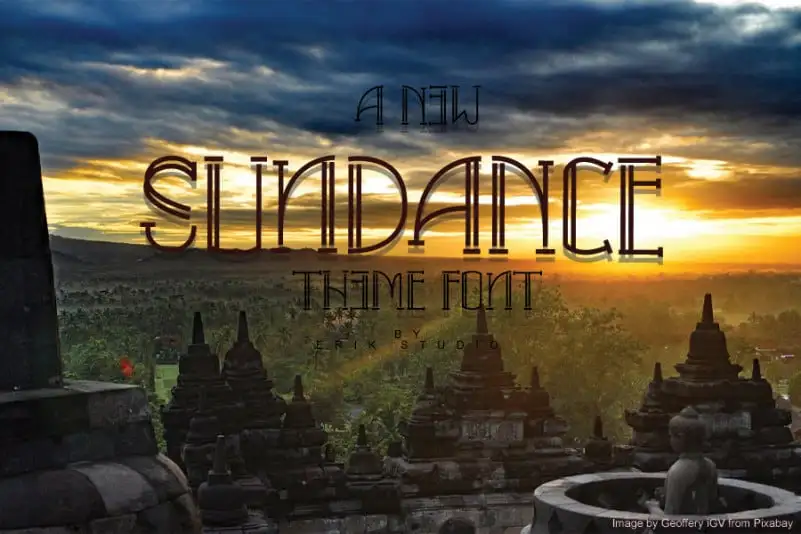
Sundance Display Font – Fonte Grátis
Sundance Display Font
A Sundance Display Font é uma nova adição para designers amadores e profissionais que buscam dar vida a suas criações com estilo. Inspirada por elementos de design outdoor, essa fonte desliza pela tela como um balão de futebol vibrante em pleno céu azul. Suas letras expressivas e únicas criam um contraste atraente para projetos que buscam destacar-se do resto da galáxia digital. Com o Sundance Display Font, cada projeto ganha uma essência moderna e original, tornando-as uma opção irresistível para quem deseja trazer vida a seus esboços. Seja um broche de design editorial ou uma capa para seu próximo filme independente, essa fonte é ideal para transformar suas ideias em realidade. Adicione o Sundance Display Font à sua próxima criação e observe como ele torna tudo mais especial!